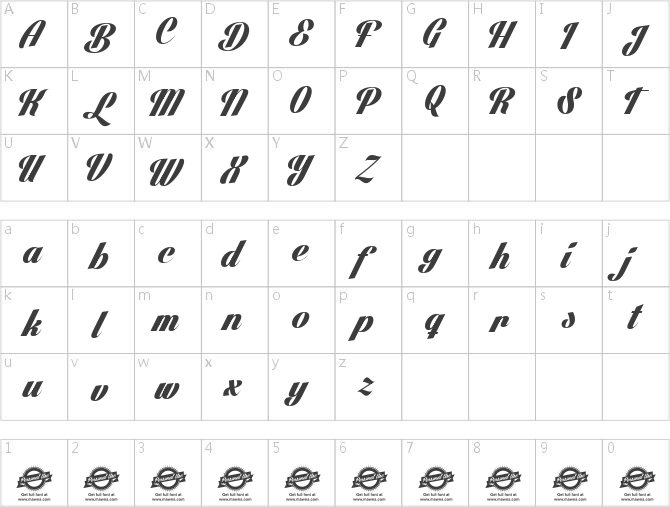
Lighthouse Personal Use 詳情頁
Lighthouse Personal Use字體字庫是一款讓人賞心悅目、百看不厭的英文字體,適合各類廣告和產(chǎn)品包裝設(shè)計應(yīng)用,字體大小0.07MB,格式為ttf字體,上傳用戶是文生電腦,作者/版權(quán)方為未知